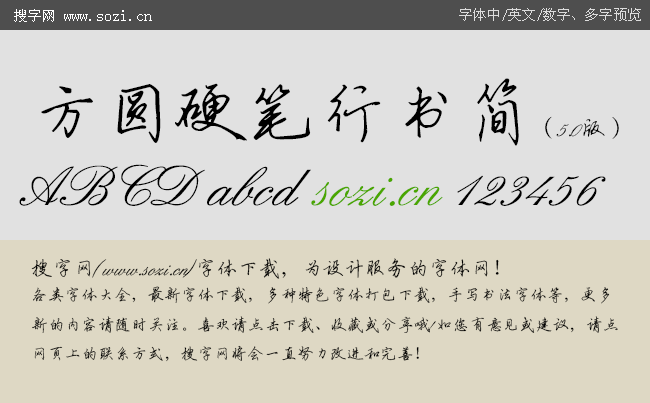
方圓硬筆行書簡(jiǎn)
搜字網(wǎng)提供一款方圓硬筆行書簡(jiǎn)中文書法字體下載,方圓硬筆行書簡(jiǎn)是一款手寫風(fēng)格的鋼筆書法字體,字體書寫流暢,字形大方,整體效果十分出色,適合應(yīng)用于廣告設(shè)計(jì)、名片設(shè)計(jì)、包裝印刷、產(chǎn)品設(shè)計(jì)等應(yīng)用。